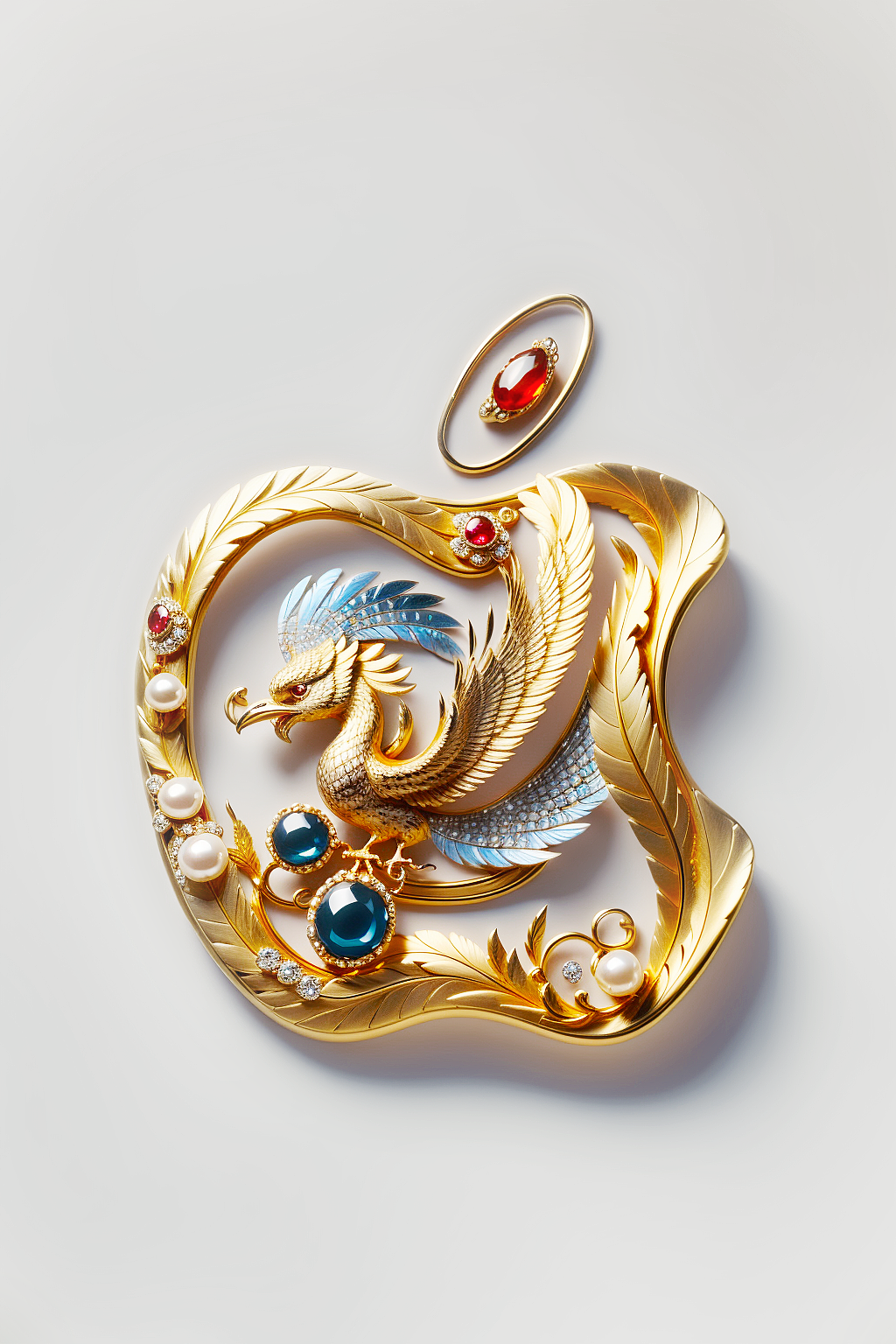
龙凤呈祥字体模型分享
在中华文明的浩瀚星空中,龙与凤无疑是两颗最璀璨的星辰。它们不仅是神话传说中的神秘生物,更是中华民族精神图腾的象征。今天,我们将带您一起探索一款以“龙凤呈祥”为主题的字体模型---好机友龙凤呈祥模型,这款字体模型具备高度的实用性和可塑性,无论是用于节日贺卡、婚礼请柬还是商业广告,都能展现出其独特的审美价值和美好寓意。